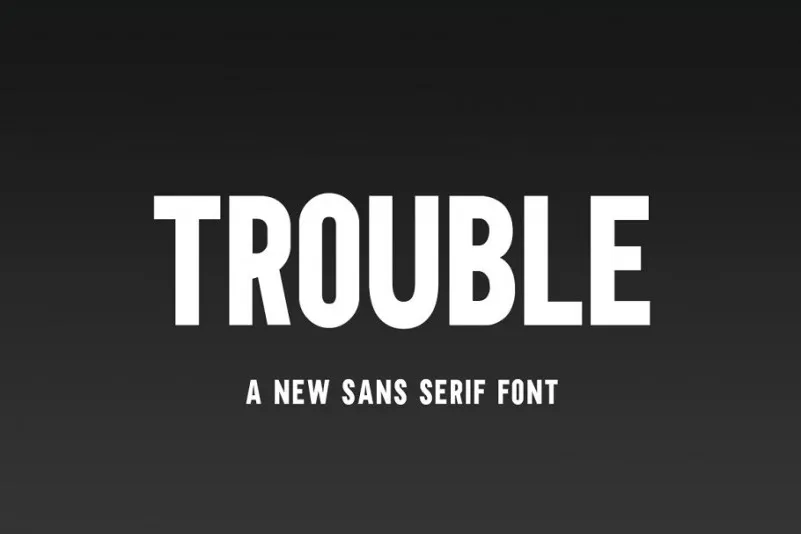
Trouble Sans Serif Font – Download Grátis
Agradecemos pelo seu interesse em Trouble Sans Serif Font! Esta nova fonte sans serif foi criada para headlines ousados, como grandes cartazes de filmes, anúncios ou editoriais, tornando esta tipografia perfeita para criar headlines chamativas e editoriais impactantes. Ela foi projetada e compartilhada pela Salt & Pepper Designs. Trouble Sans Serif Font da Salt & Pepper Designs não apenas oferece uma adição ousada a seu trabalho, mas também possui um charme próprio que se destaca em meio às scripts elegantes. Esta fonte sans serif é perfeita para aqueles que desejam dar uma nova cara à suas criações e ainda querem manter o equilíbrio entre modernidade e sofisticação. Enjoy your new typeface!